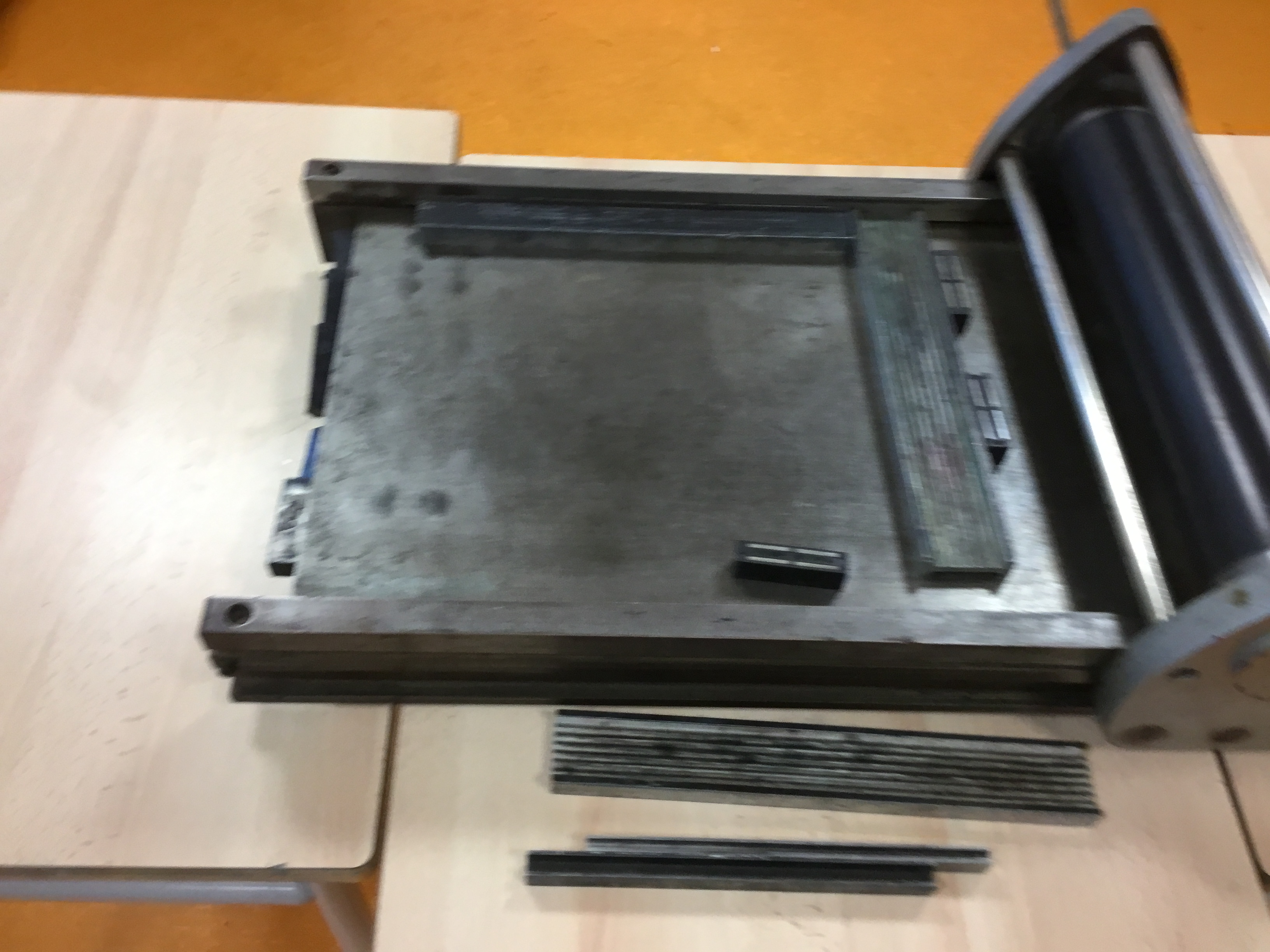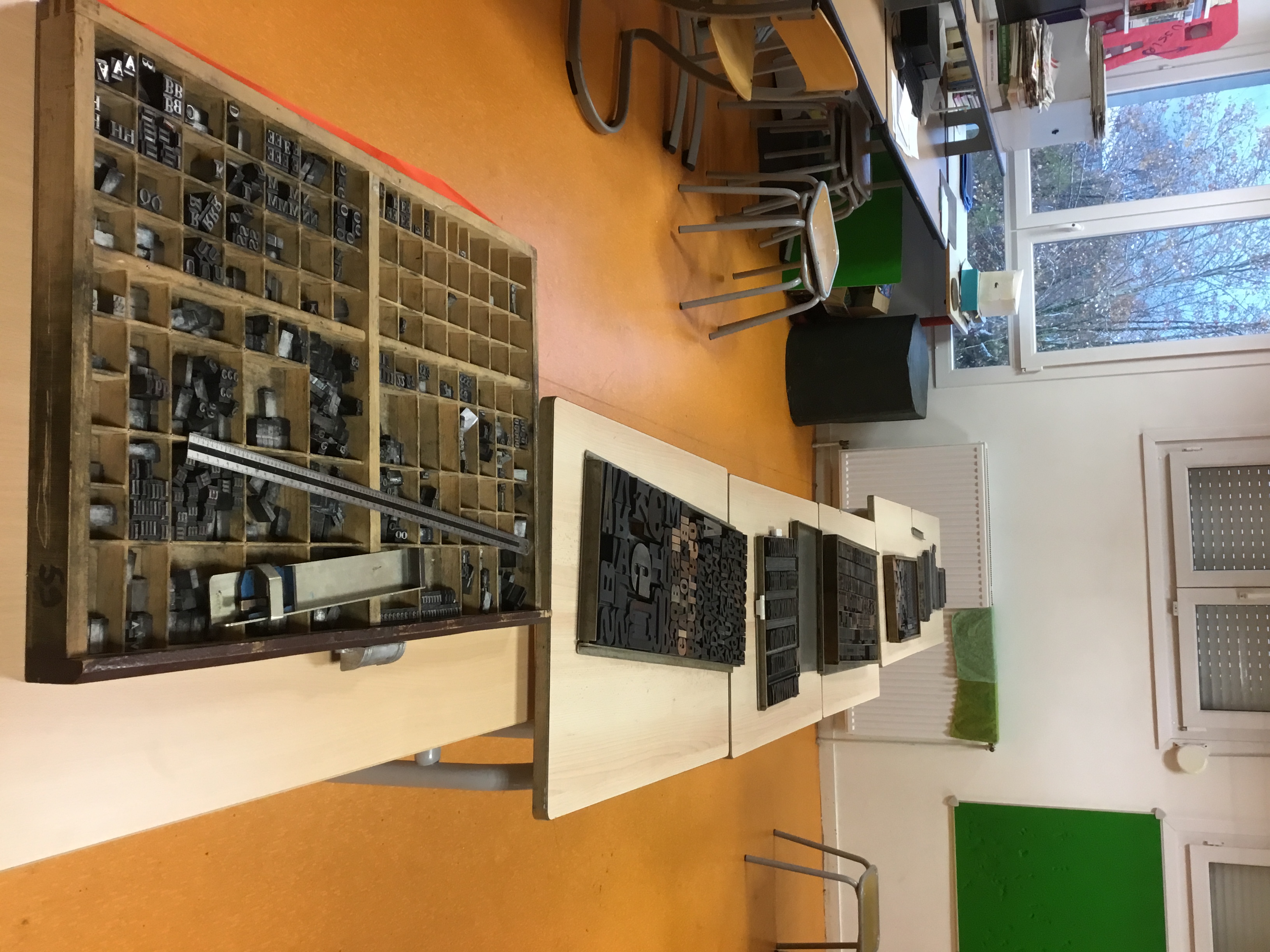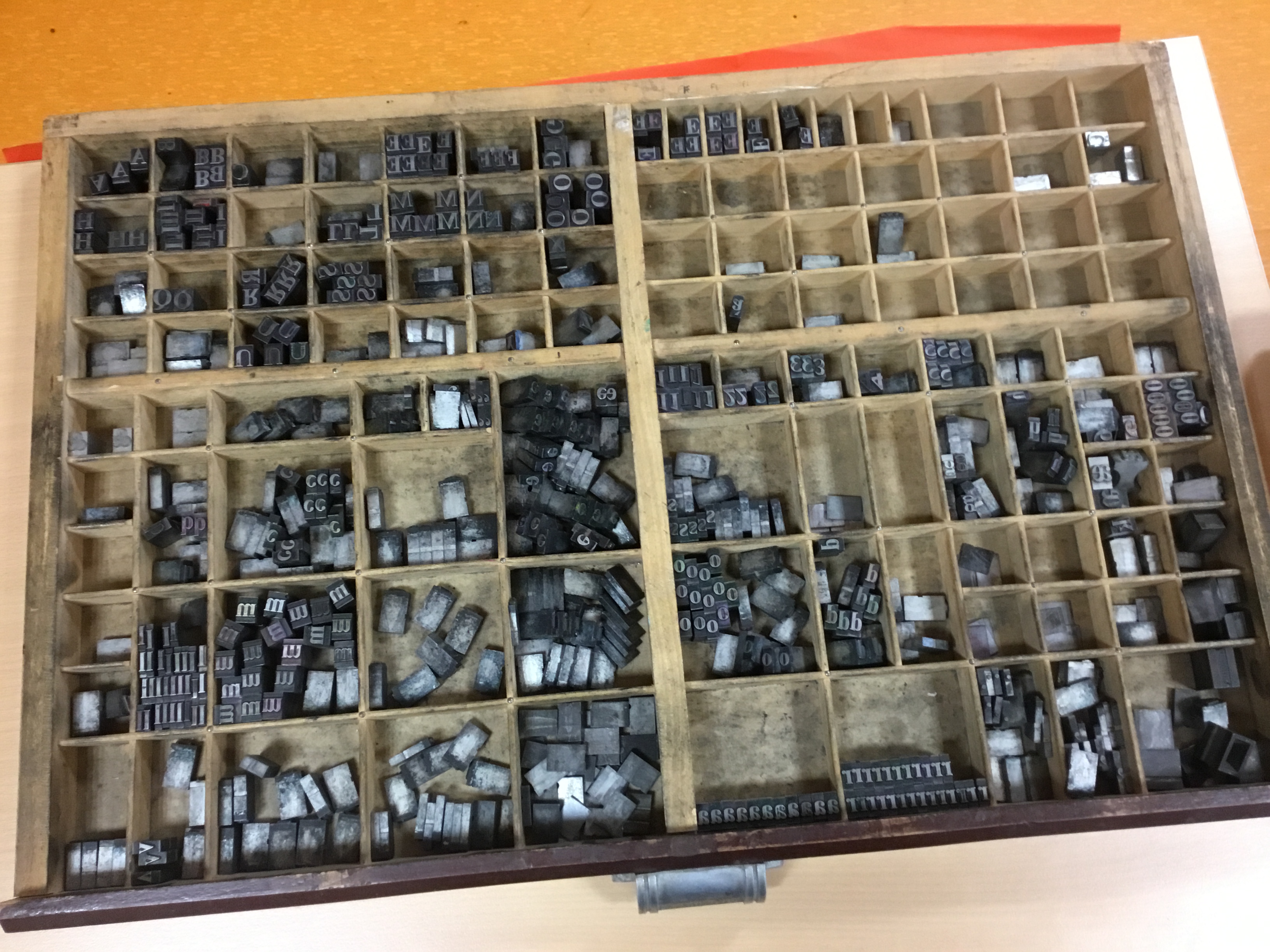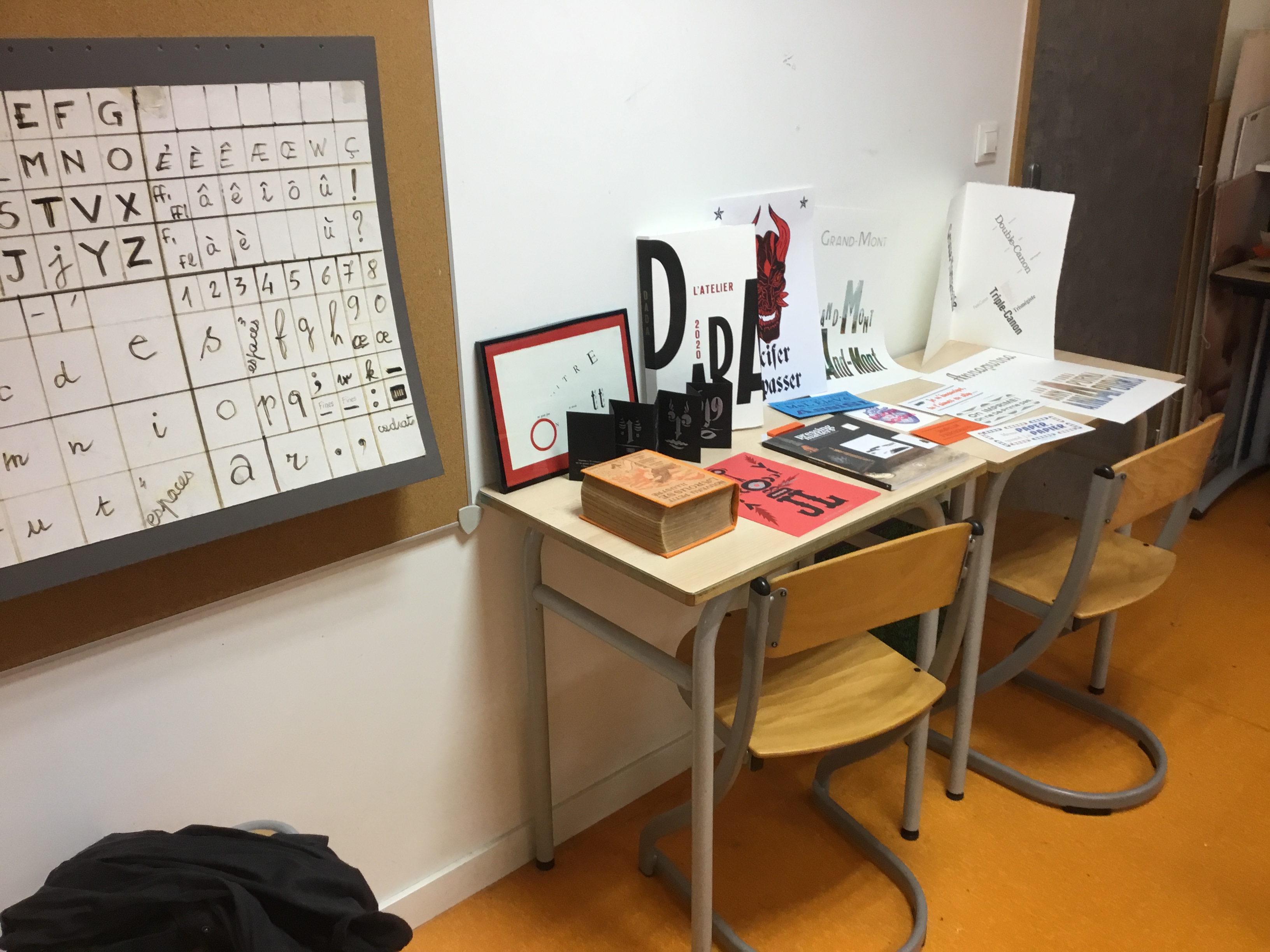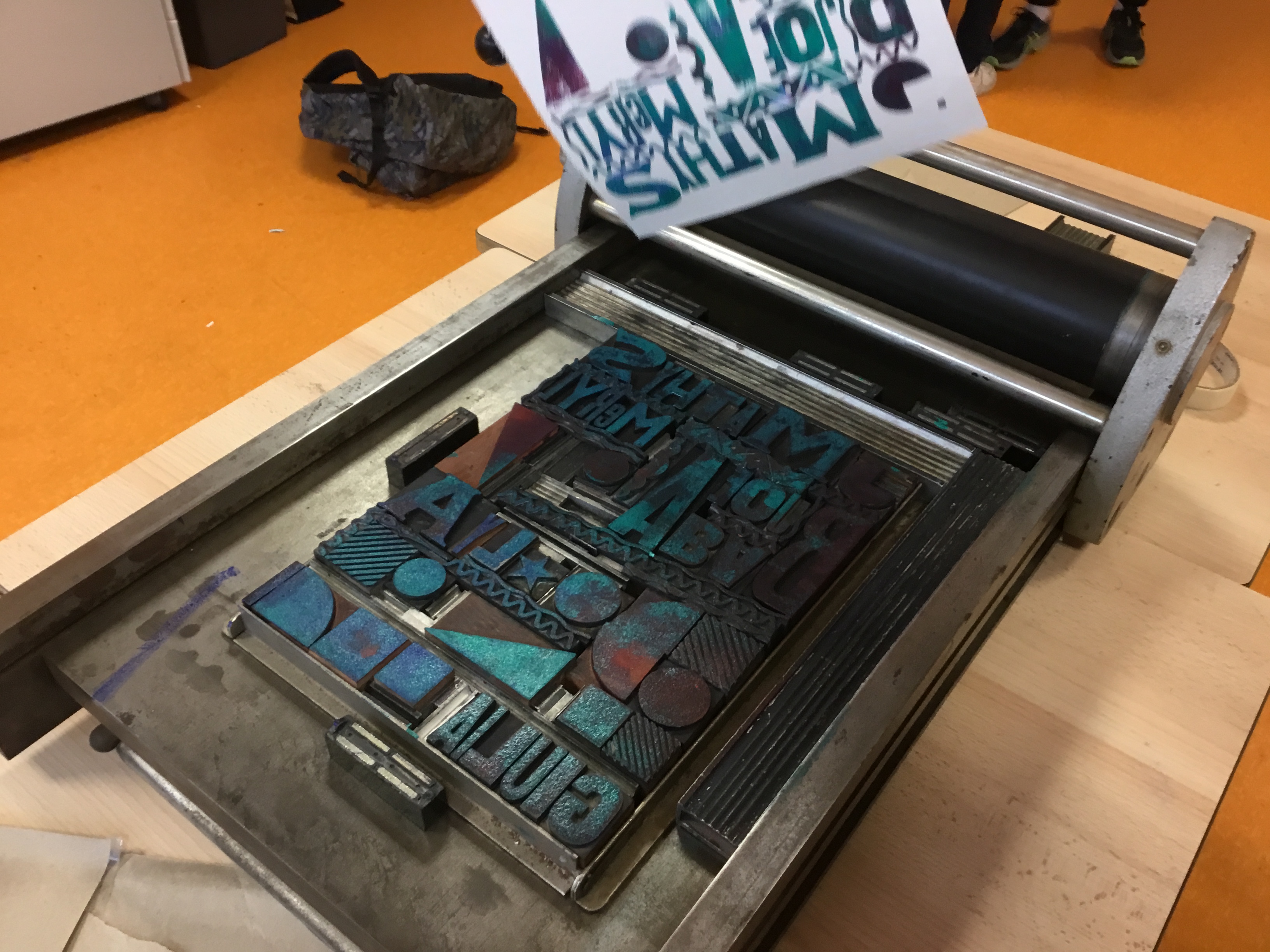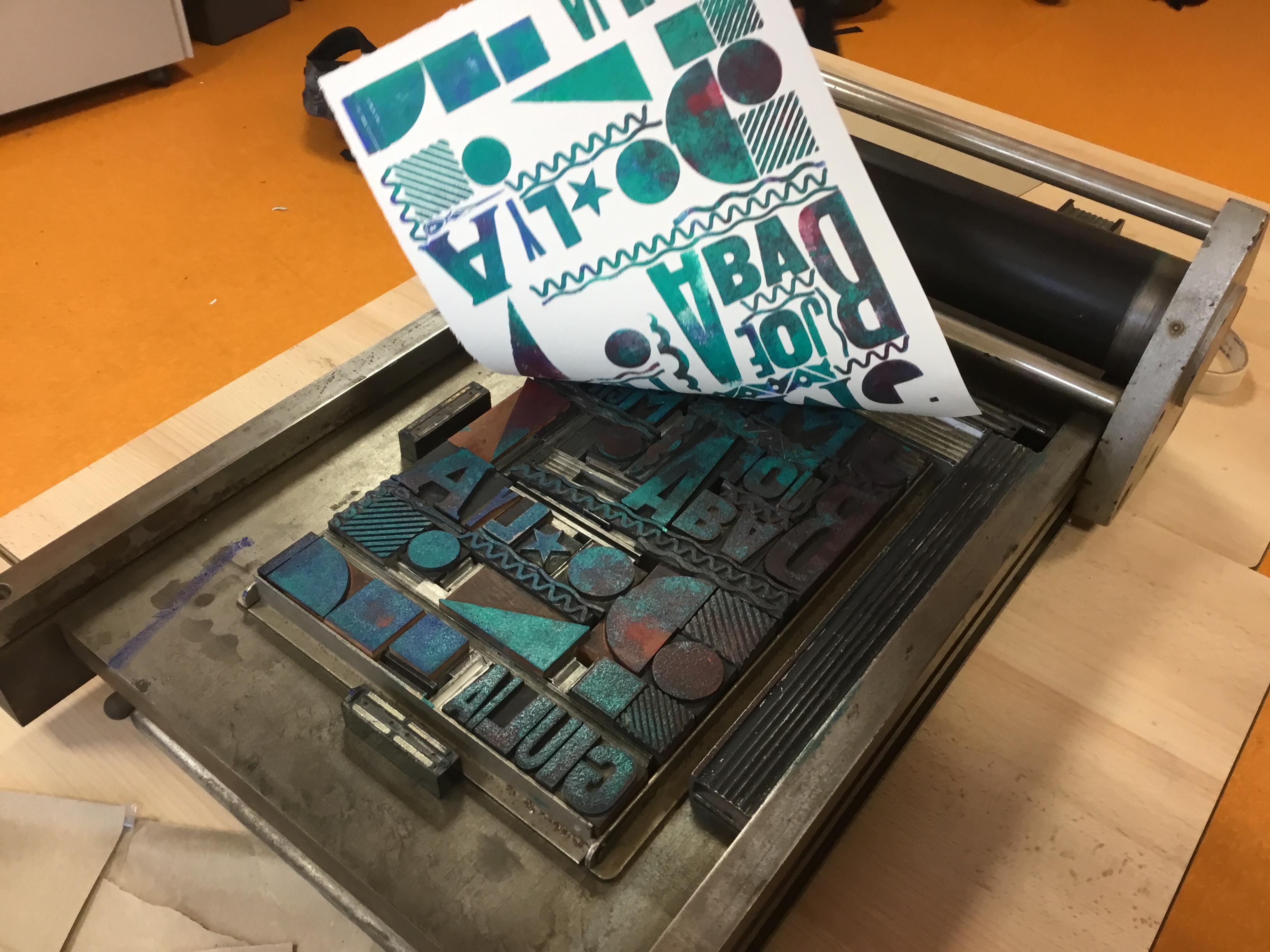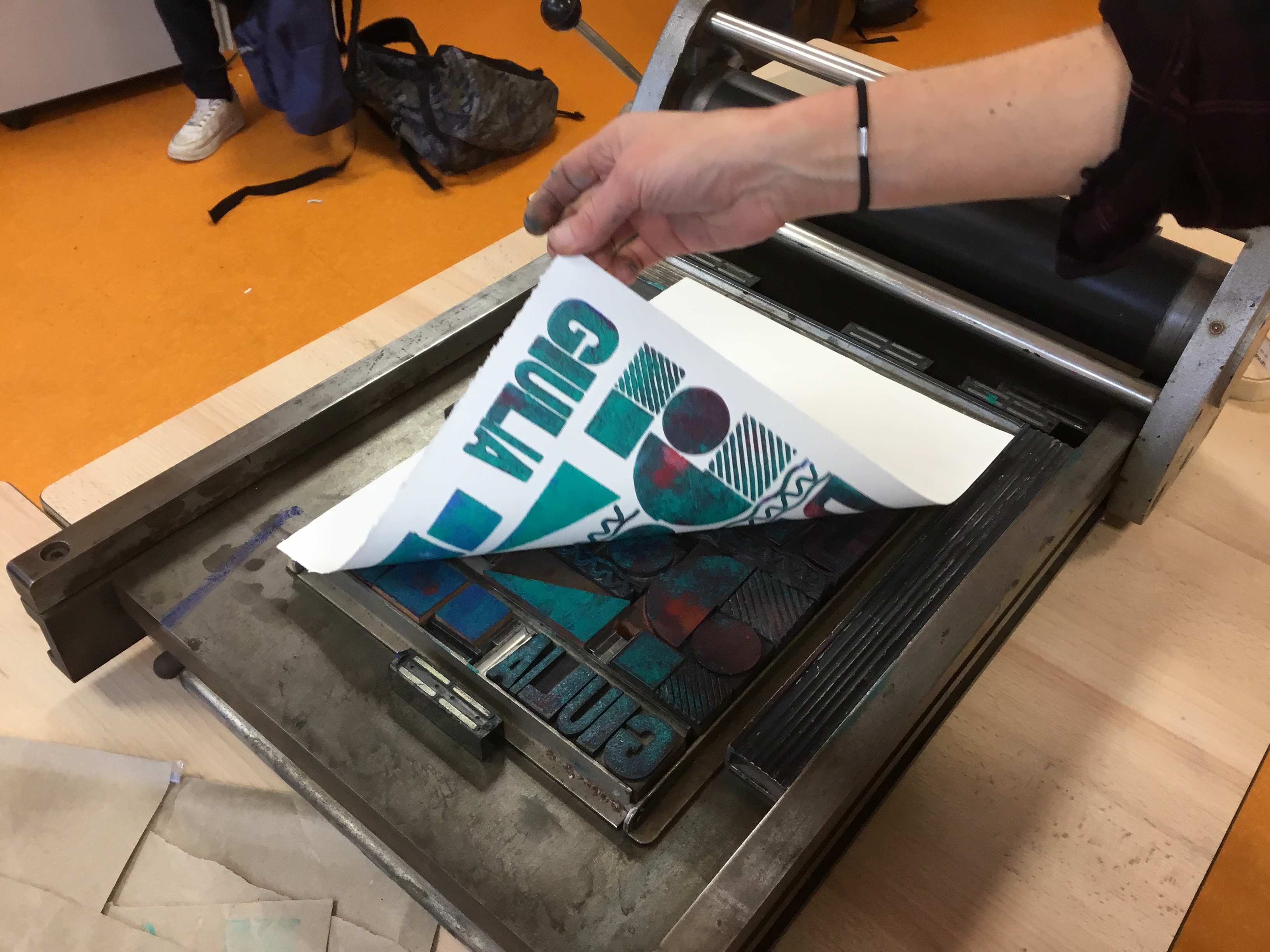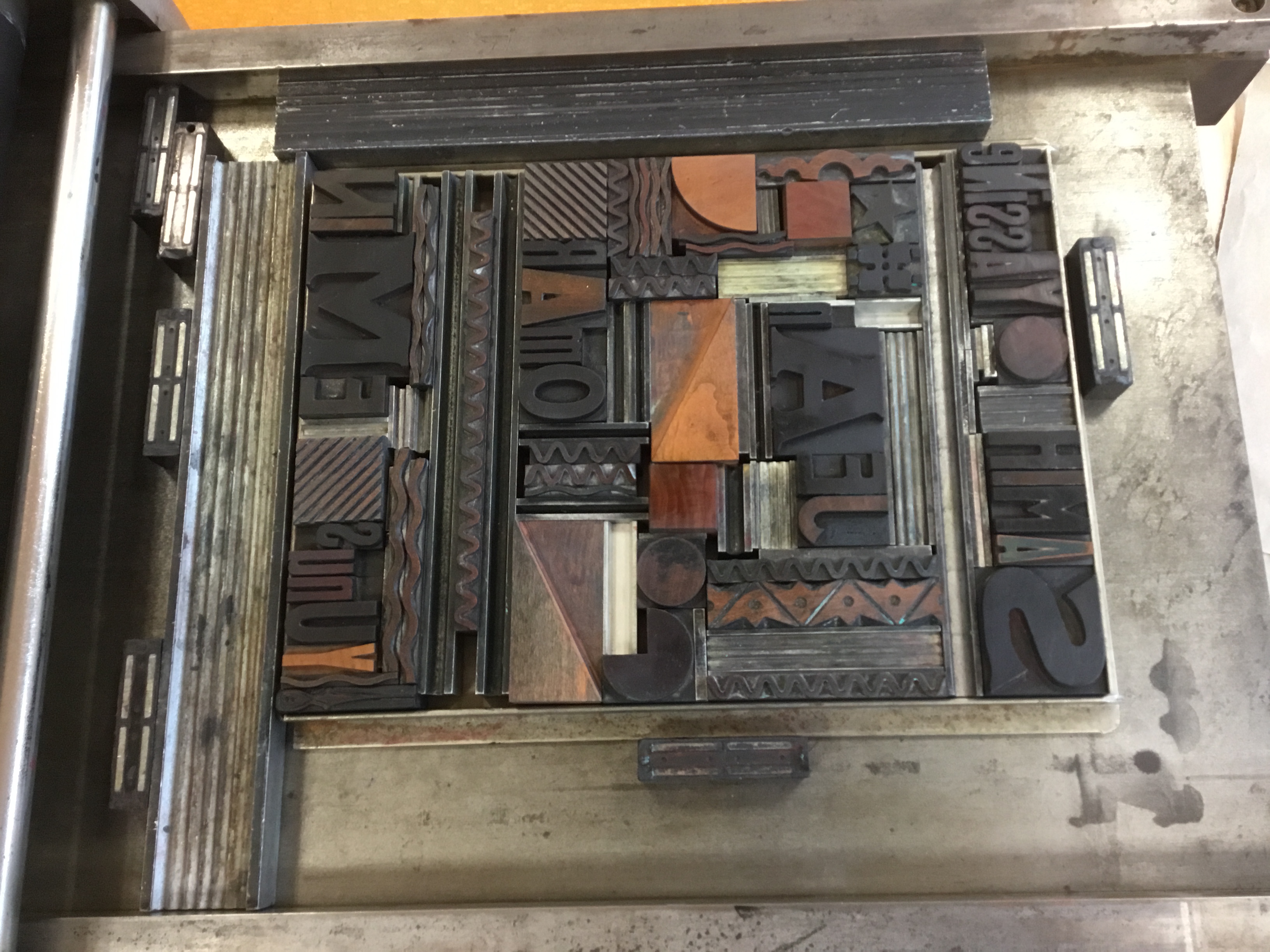
Atelier typographie pour toutes les classes de 5e et 4e
Les élèves ont pu s’initier à la typographie grâce au matériel de l’Atelier de Conflans et l’aide de Nathalie Torre, de la découverte de cette technique héritée de Guttenberg vers une ouverture plus artistique.